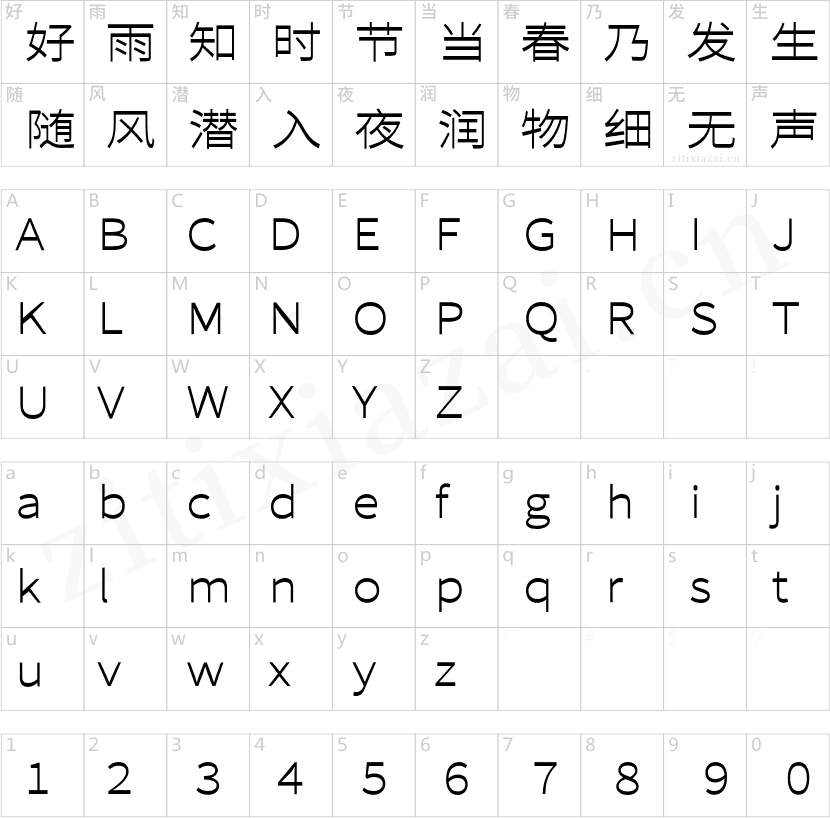
寒蝉无机体WideRegular
寒蝉无机体WideRegular,这款字体结构工整、笔画清晰,兼顾美观与易读性,适用于标题、正文、海报、包装、LOGO 等多种场景。字形优雅稳定,风格百搭耐看,适配日常排版与创意设计,让文字呈现更舒适、更具质感。寒蝉无机体WideRegular一笔一画,皆是细节,以均衡的比例、流畅的线条打造舒适视觉体验,字形端正大气,风格简约现代。无论是商业设计、品牌宣传还是日常排版,都能轻松驾驭,让文字更有格调与力量。寒蝉无机体WideRegular字体下载。
寒蝉无机体是基于思源黑体进行逆反差美术风格字体探索,尝鲜版。